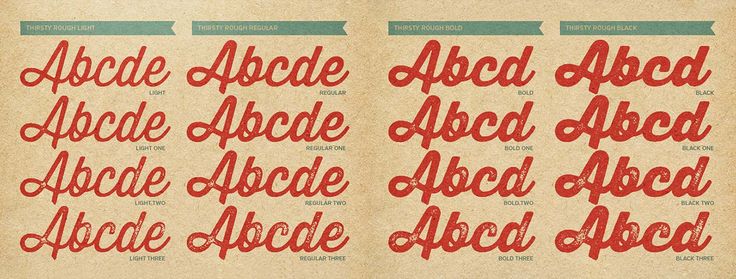
25 бесплатных ретро-шрифтов
Ретро-шрифты — это ключевой элемент ретро-дизайна, который способен перемещать аудиторию во времени, поэтому важно выбрать шрифт, отражающий эпоху, которую вы представляете. С правильным шрифтом вы можете добавить возраст, текстуру и глубину ваших проектов.
1. Stiff Staff
Этот декоративный бесплатный шрифт возвращает нас в Германию или СССР. Использование дизайнером Бориславом Петровым геометрических каналов, конструктивизма и строгого индустриального модернизма, дает нам почувствовать себя в видеоиграх.
2. Gradientico
Если вы заинтересованы в создании печатных изданий начала 1990-х, попробуйте Gradientico. Этот шрифт отлично выглядит благодаря великолепному колючему полутоновому градиенту, как будто он только что вышел из точечного матричного принтера.
3. Haike
Вдохновленный Moore Computer — шрифтом 1968 года, разработанным для использования с оборудованием для автоматической проверки и считывания документов, — Haike от Otto Maurer Design — это сказочно ретро-будущее, имеющее девять весовых коэффициентов для всех видов использования. Это бесплатно для личного использования; для коммерческого использования вам понадобится лицензионная версия, которая поставляется с дополнительными функциями Opentype.
4. Haarlem Deco
Создатели Haarlem Deco описывают шрифт как «классический ретро—все-заглавные буквы-без засечек» с оттенком ар-деко. Вдохновленный старыми евро-американскими вывесками и рекламой, он доступен в виде бесплатной демо-версии с ограниченным количеством символов;
5.
West Side
Вдохновленный дизайном постеров ручной работы и иллюстрациями 1980-х годов, возможно, с небольшим намеком на Саула Басса, West Side — это блочный экранный шрифт, созданный вручную в студии Artimasa Studio. Он большой и жирный, с острыми краями и бесплатный как для личного, так и для коммерческого использования.
6. Palm Canyon Drive
Вы можете получить бесплатную версию Palm Canyon Drive — разработанного Эми Худ, соучредителем Hoodzpah Design Co, в сочетании с элементами ретро и винтажного дизайна — подписавшись на рассылку RetroSupply. (Вы также получите множество других элементов в стиле ретро и винтажной тематики.)
Вдохновленный южной Калифорнией середины столетия, ретро-шрифт идеально подходит для того, чтобы добавить некую доброту западного побережья США старой школы.
7. Billionaire Medium Grunge
Для стиля арт-деко, который по краям выглядит довольно грубым, Billionaire Medium Grunge — просто находка.
Это всего лишь один из шести шрифтов, составляющих полный шрифт Billionaire от JumboDesign, и вы можете получить его бесплатно, чтобы придать своей работе немного блеклую изысканность.
8. Noir
Добавьте нотку элегантности и стиля в ваш дизайн с этим красивым ретро-шрифтом Noir от дизайнера Matthias Guggisberg.
9. Frontage Condensed (Outline)
Frontage Condensed, созданный швейцарским арт-директором Юрием Заечем, представляет собой красивую семью ретро-шрифтов. Frontage Condensed идеально подходит для любого дизайна в винтажном стиле и доступен в различных вариантах, один из которых, Outline, Zaech можно загрузить бесплатно.
10. Say It Fat
Дизайнер Тимо Тицманн создал бесплатный ретро-шрифт Say It Fat. Смелый шрифт Say It Fat отлично подходит для создания привлекательных постеров в стиле ретро.
11. Portico
Созданный дизайнером Mehmet Reha Tugcu, Portico идеально подходит для любых дизайнов в стиле ретро.
12. Monthoers
Шрифт Monthoers в стиле ретро был создан графическим дизайнером Agga Swist’blnk. Она комментирует на Behance: «Monthoers — это последняя версия шрифта Rochoes, которую я сделал почти год назад. Она бесплатна для личного и коммерческого использования».
13. Hamster
Hamster — это скорописный шрифт, вдохновленный кистью и традиционными знаками. Hamster можно загрузить бесплатно как для личного, так и для коммерческого использования.
14. Lazer 84
Перенеситесь в прошлое с помощью Lazer 84. Созданный арт-директором Хуаном Ходжсоном, Lazer 84, вдохновленный 80-ми годами, представляет собой шрифт в стиле ретро, который дополнен цифрами, символами и акцентами.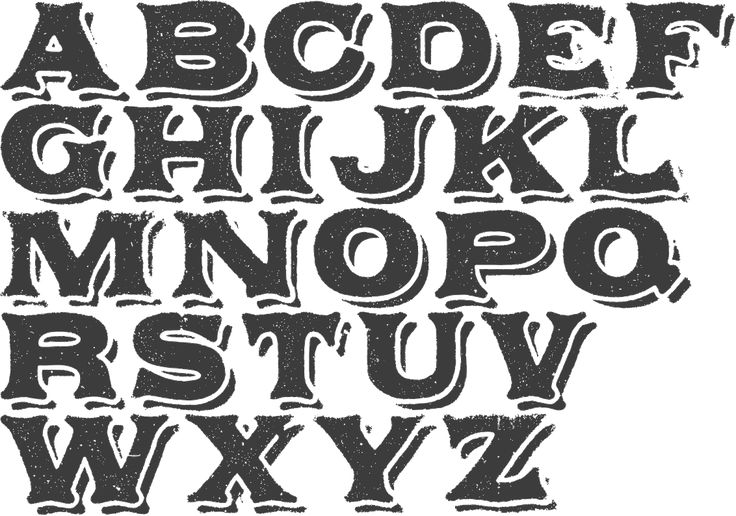
15. Ansley
Графический дизайнер Kady Jesko создал шрифт Ansley, после неудачного поиска бесплатного шрифта в стиле ретро. Jesko теперь предлагает его для бесплатной загрузки как для личного, так и для коммерческого использования.
Это семейство шрифтов от Vintage Voyage D.S . с крутыми ретро-дополнениями и 7 стилями слоев — все, что вам нужно, чтобы без особых усилий создавать плакаты, открытки, этикетки, вывески и многое другое в стиле 50-х годов.
Luckiest Guy Pro
Просто включите автоматические лигатуры и наблюдайте, как каждая пара букв всегда идеально соединяется.
Используйте его на заголовках, плакатах, бирках, логотипах и этикетках для непринужденной, но игривой атмосферы.